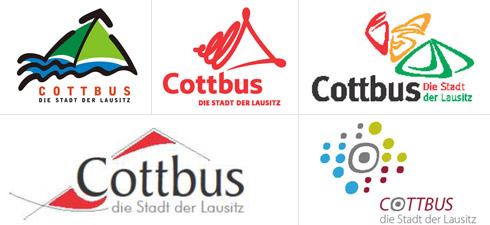
Im Januar 2009 versuchte die Stadt Cottbus, mit einer neuen Bildmarke auf sich aufmerksam zu machen. Schon die Ausschreibung ließ Schlimmes befürchten, doch das Ergebnis übertraf alle Erwartungen. Fontblog berichtete mehrfach:
»Der Entwurf scheiterte am Protest von Bürgern und Fachleuten.« schreibt die Lausitzer Rundschau heute abend auf ihrer Webseite. Und: »Jetzt stellt Oberbürgermeister Frank Szymanski (SPD) fünf neue Entwürfe zur Debatte.« Diesmal dürfen die Cottbuser mitentscheiden.
»Obwohl wir keinerlei Vorgaben gemacht haben, spielen viele Entwürfe mit dem Motiv der Pyramiden«, zitiert die Tageszeitung Szymanski aus der Präsentation. Neben der Pücklerschen Gartenkunst hätten die Designer das Theater als Wahrzeichen der Stadt hervorgehoben. Ein anderer Entwurf spiele mit der Idee, »die Stadt der Lausitz« als Kern einer vielfältigen Region darzustellen. Alle fünf Bildmarken könnten, so die Zeitung, je nach Nutzungszusammenhang mit Ergänzungen wie »Stadt der Wissenschaft«, »Drehscheibe zwischen Ost und West« oder »Universitätsstadt« genutzt werden.
Details zur geplanten Marketingstrategie, den einzelnen Entwürfen und Variationen wird die Lausitzer Rundschau in den kommenden Tagen auf ihrer Internetseite vorstellen.